Tipografi logo bukan hanya soal mudah dibaca tetapi juga harus menarik sehingga memikat audiens. Gaya font yang digunakan terkadang mengkombinasikan dua font atau lebih agar menciptakan kontras. Kontras kombinasi font dalam logo akan menciptakan hirarki visual dan meningkatkan daya tarik visual logo.
Penting sekali untuk logo memiliki kombinasi font yang kontras sehingga desain lebih menarik. Kontras font akan membuat desain logo lebih menarik perhatian sehingga bisa menciptakan identitas visual yang kuat. Kombinasi dua gaya font berbeda akan efektif menciptakan tipografi yang kontras.
KONTRAS GAYA FONT
Kontras dalam tipografi sendiri berarti kombinasi gaya huruf yang terlihat berbeda baik dari ukuran, bentuk huruf hingga ketebalannya. Tujuan dari menciptakan kontras pada logo adalah agar terlihat jelas perbedaan nama brand dan sub judul atau taglinenya. Sementara itu contoh kombinasi gaya font yang kontras seperti:
- Serif vs Sans Serif
- Bold vs Light
- Besar vs Kecil
- Formal vs Playful
Dengan membedakan jenis font makan kombinasi akan menciptakan kontras. Meski begitu font yang sama bisa kontras dengan menggunakan perbedaan ketebalan gaya huruf. Ukuran dan kesan yang diciptakan dari gaya huruf juga berguna menciptakan kontras yang menarik.
MENGAPA KONTRAS PENTING DALAM DESAIN LOGO?
Untuk menciptakan desain logo yang lebih menarik, gunakan kombinasi dua gaya tipografi yang berbeda. Kontras harus dibuat jelas agar desain logo lebih menarik dan unik. Ada beberapa kelebihan dari menciptakan kontras kombinasi font logo seperti:
Menarik Perhatian Visual
Desain logo akan jauh lebih menarik perhatian dengan menggunakan kombinasi font yang kontras daripada hanya menggunakan font yang sama atau mirip. Semakin kontras gaya fontnya, logo akan tampil semakin menarik perhatian visual logo. Kontras font seperti sans serif dan script akan menciptakan fokus pada nama brand.
Menampilkan Hirarki Visual
Salah satu tujuan penting dalam menciptakan kontras tipografi desain logo adalah untuk menciptakan hirarki visual. Dengan perbedaan gaya font seperti jenis font dan ukuran huruf akan menonjolkan teks utama. Font nama brand bisa lebih menarik perhatian utama daripada teks sub judulnya.
Menciptakan Keseimbangan dan Dinamika
Dengan mengkombinasikan dua gaya font yang kontras, ini juga berguna menciptakan keseimbangan visual. Kontras gaya huruf bisa membuat desain tampil lebih seimbang, serta menciptakan dinamika yang menarik.
Memperkuat Karakter dan Nilai Merek
Font dalam logo bisa merepresentasikan karakter atau emosi tertentu yang mewakili merek. Dengan menggunakan dua gaya tipografi yang kontras maka akan semakin memperkuat karakter brand. Kombinasi kedua font yang kontras dapat dipilih sesuai karakter dan nilai brand agar relevan.
5 CONTOH LOGO DENGAN GAYA FONT KONTRAS
Kontras font yang dikombinasikan dalam desain logo cukup beragam, terkadang banyak menggunakan perbedaan ketebalan huruf. Adapula yang fokus menciptakan kombinasi dua jenis font berbeda dengan ukuran teks yang cukup kontras. Namun tetap pemilihan font yang kontras harus disesuaikan dengan karakter dan nilai brand.
Logo Sigma Coffee & Food
Tipografi untuk desain logo bisnis kopi dan makanan tersebut menggunakan gaya font tulisan tangan yang tebal. Font handwritten tebal tersebut memiliki garis huruf yang halus dan bersih. Gaya huruf menciptakan kesan ramah dan bersahabat, cocok digunakan pada font logo food & beverage.
Kontras font logo tercipta karena memiliki kombinasi dua gaya font berbeda yaitu handwritten dan serif. Selain menggunakan jenis font berbeda, kontras juga tercipta dari ketebalan huruf yang berbeda. Nama brand memiliki font tebal dan ukuran yang lebih besar sehingga kontras dengan tagline atau sub judul dalam logo tersebut.
Logo Clockin Coffee
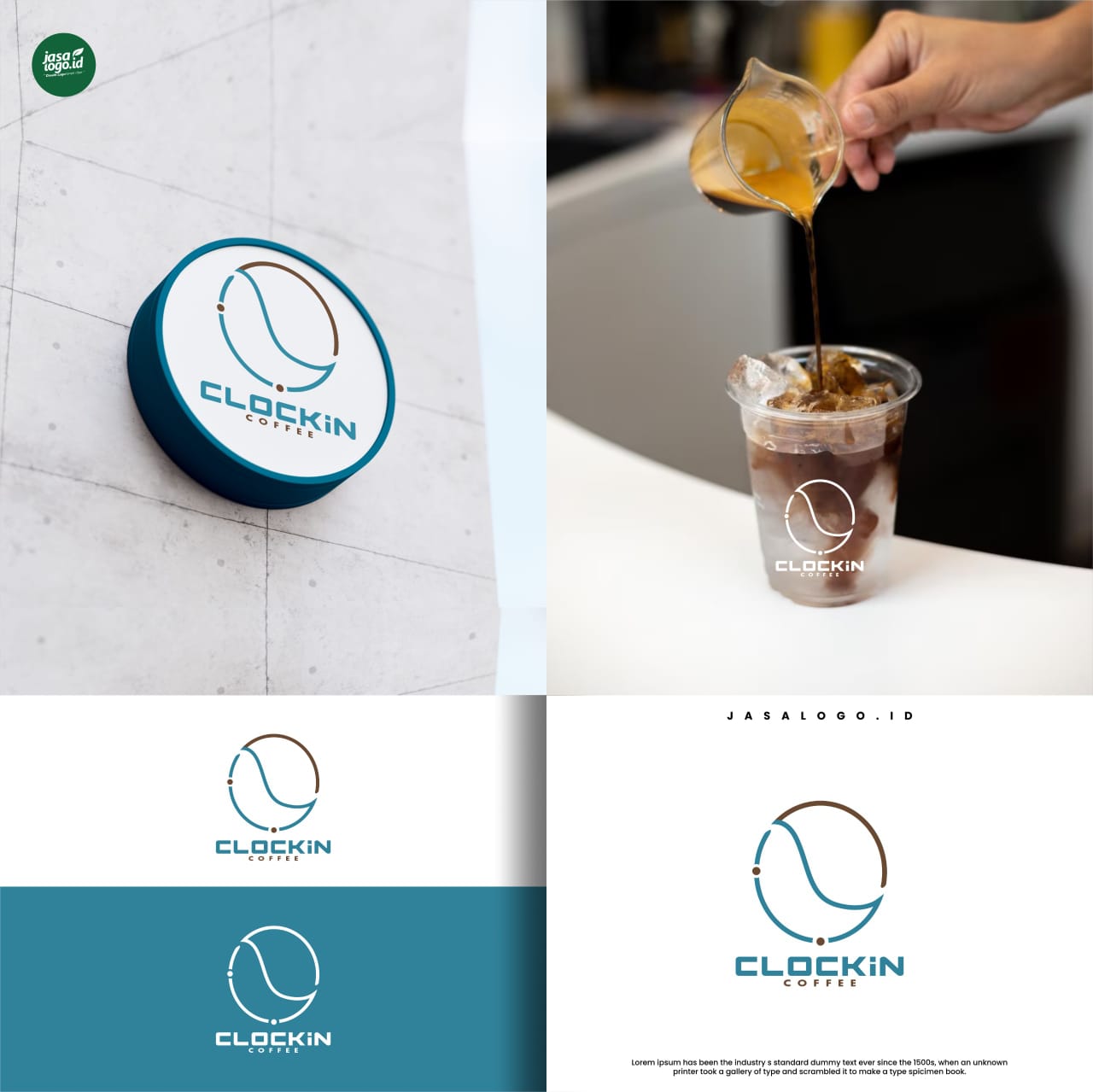
Jenis font yang sama juga bisa menciptakan kontras karena ada banyak variasi gaya hurufnya seperti font sans serif. Font sans serif yang digunakan dalam desain logo memiliki gaya huruf yang sederhana dan geometris. Meski kedua font dari jenis font sans serif tetapi memiliki gaya huruf kontras.
Font sub judul memiliki gaya huruf sans serif sederhana dan tidak begitu kaku, berbeda dengan font utama yang memiliki gaya geometris. Font geometris menciptakan desain brand berkesan modern dan minimalis. Kombinasi jenis font yang sama dengan gaya huruf berbeda juga efektif menciptakan kontras pada logo.
Logo Ibil Publishing
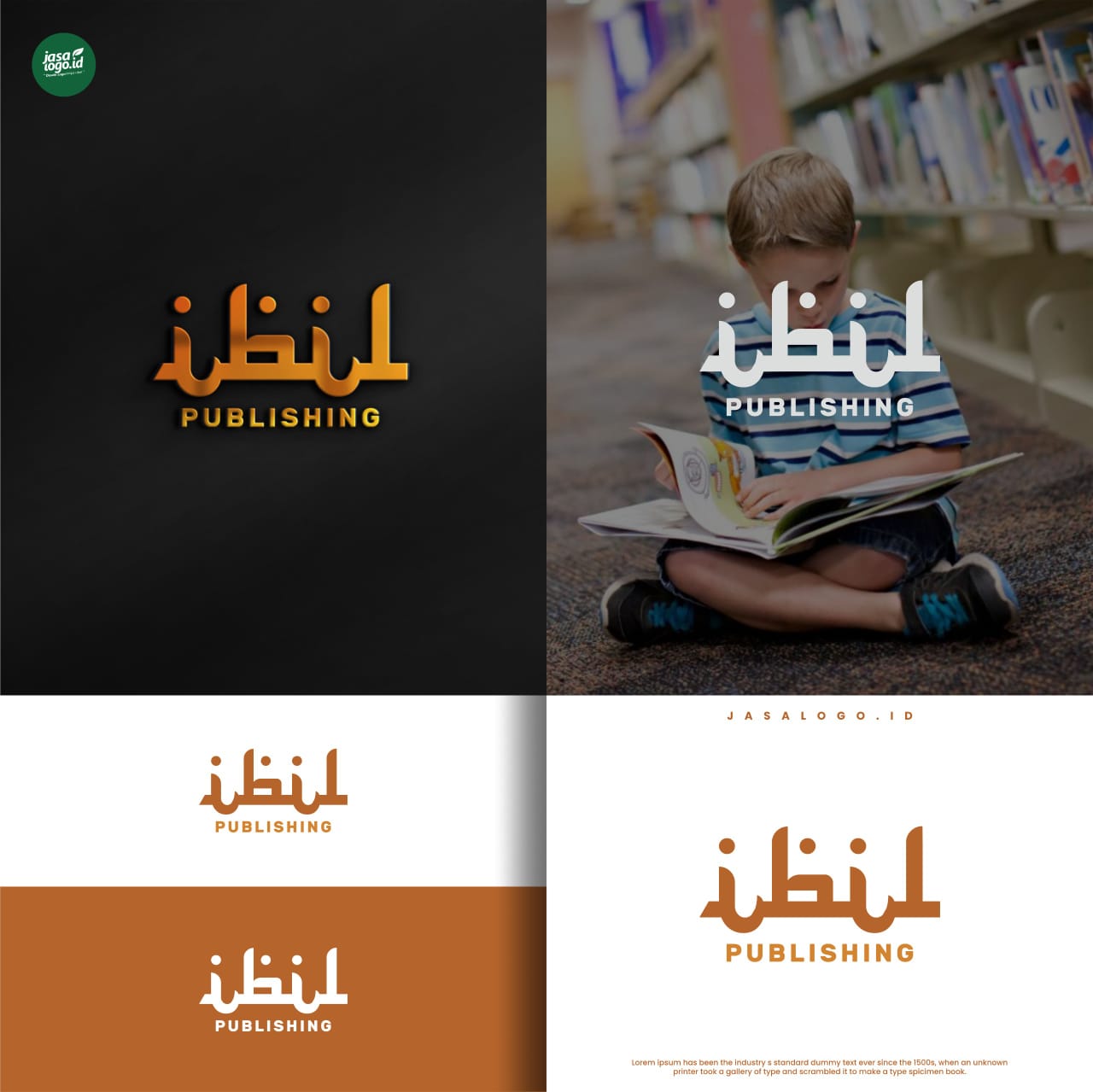
Gaya font dengan style font dari huruf tertentu bisa menciptakan kontras dengan gaya huruf alphabet biasa. Font logo tersebut mengkombinasikan dua gaya tipografi yang cukup kontras. Logo memiliki gaya tipografi dari font arabic dan font sans serif sederhana yang kontras.
Tipografi font tersebut mengkombinasikan gaya huruf Arab dan font biasa sehingga menciptakan tipografi yang unik. Perbedaan gaya font tersebut efektif menciptakan hirarki visual dan meningkatkan daya tarik visual. Gaya huruf arabic yang digunakan biasanya merepresentasikan bisnis terkait islam atau produk arab.
Terkadang demi menciptakan desain logo yang unik, sampai harus menggunakan font yang unik dan sulit dibaca. Jangan menggunakan gaya font yang rumit dalam logo demi menciptakan kombinasi font yang kontras. Kontras gaya font harus tetap mempertahankan keterbacaan yang jelas agar nama brand mudah dikenali.
Kombinasi dua font dalam desain logo bertujuan menciptakan kontras dan tampilan yang unik. Kontras gaya font berguna meningkatkan daya tarik visual dan memperkuat identitas brand. Bedakan jenis font, gaya huruf, ukuran huruf dan ketebalannya agar mencipta desain logo yang kontras.